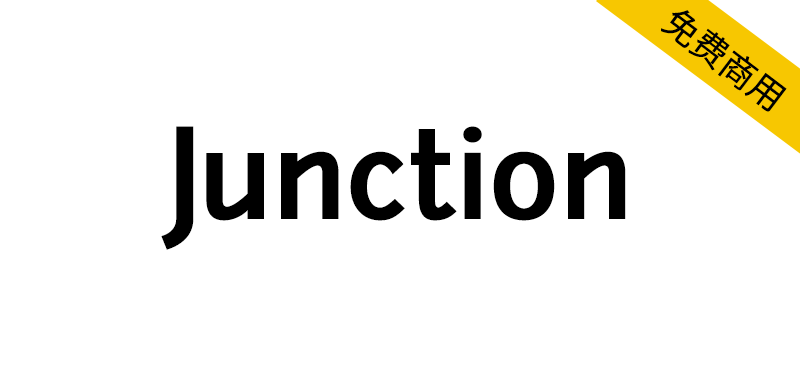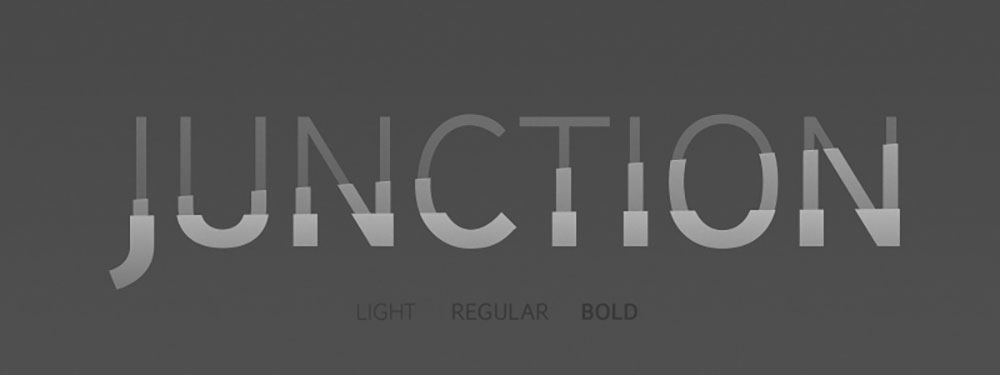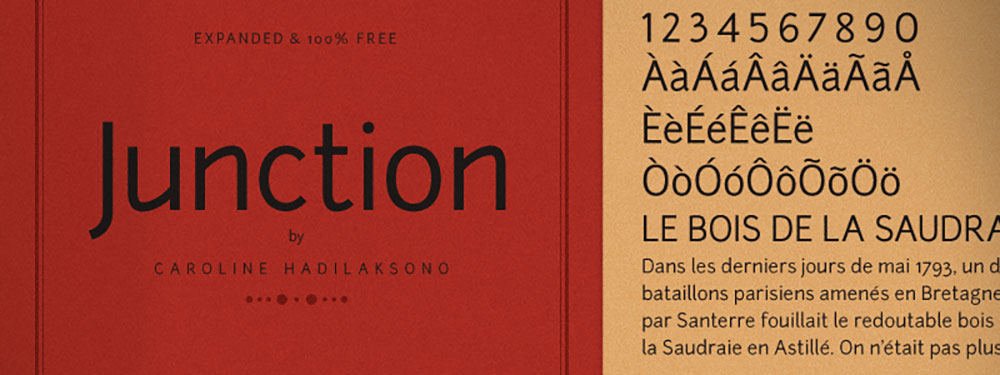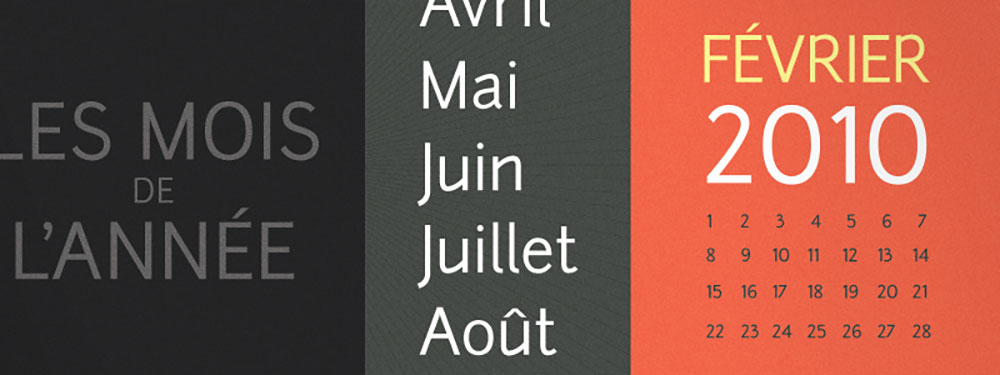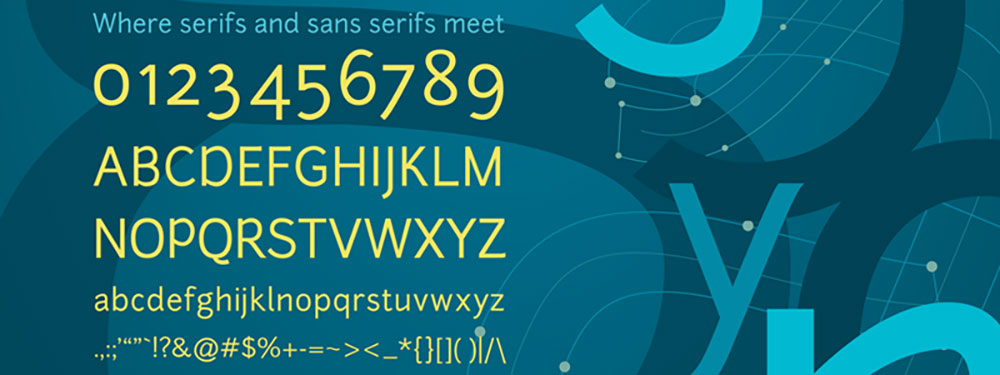
Junction 是一款人文主义无衬线字体,也是 The League of Moveable Type 发起的首个开源字体项目。2014年,该字体经过更新,新增了字重(细体/粗体)并扩展了对多语言的支持。
Junction is a a humanist sans-serif, and the first open-source type project started by The League of Moveable Type. It has been updated (2014) to include additional weights (light/bold) and expanded international support.